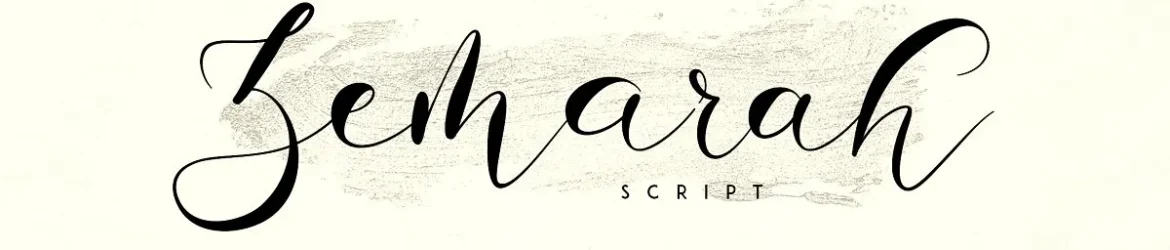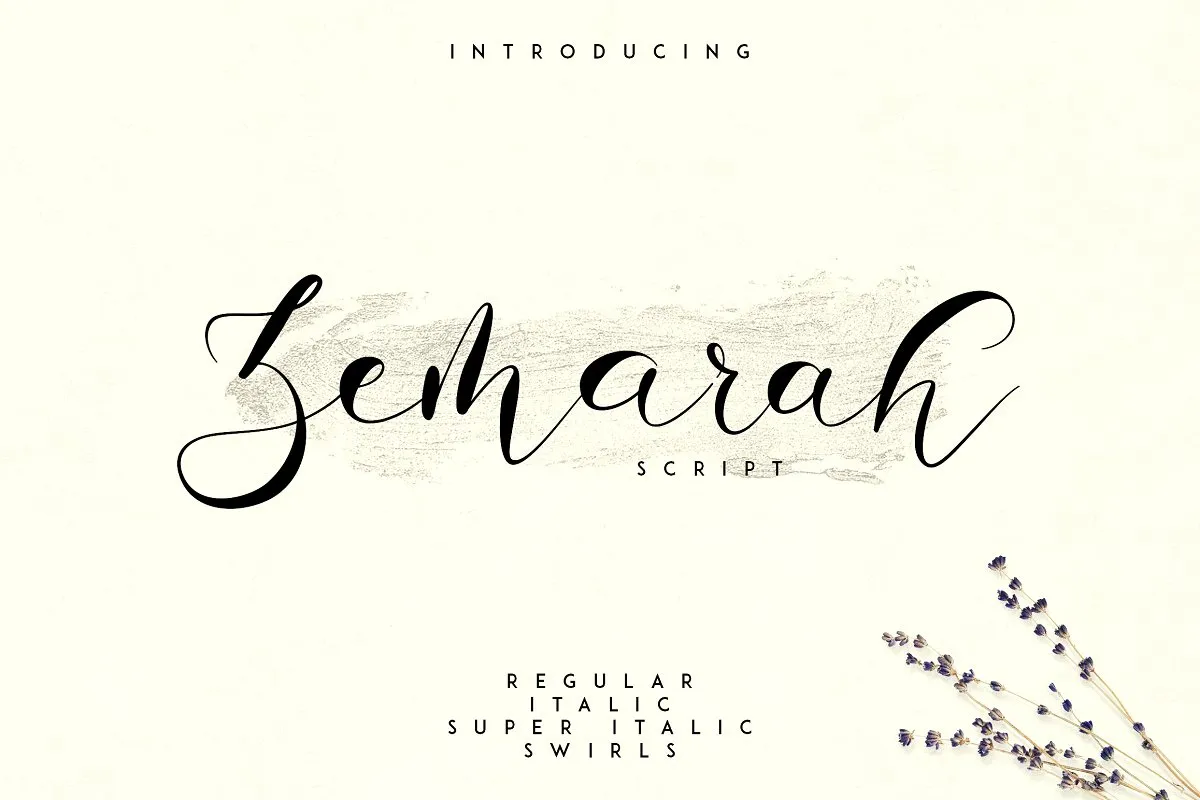
Zemarah Script Font – Fonte Grátis
Zemarah Script Font
A Zemarah Font é uma nova criação do design de Hamilton, oferecendo ao usuário um estilo elegante de calligrafia que se destaca por sua simplicidade e classe. Esta fonte foi pensada para ser simples e única, não sendo apenas mais um tipo de letra elegante. O designer introduziu três estilos nesta fonte: chamadas com borbulhantes e suavidades, além do apoio multilíngue que a torna ainda mais versátil. O estilo da Zemarah é tão singular que se destaca em grandes e pequenos tamanhos de texto. É uma opção ideal para designers gráficos e escritores, que buscam adicionar um toque único e sofisticado ao seu projeto visual. Com o Zemarah, você pode experimentar diferentes texturas e sensações em seus projetos com uma fonte versátil que vai desde as letras mais sutis até os espaçamentos mais amplos. Adquirir a Zemarah Font é garantir um estilo único para suas obras de design, tornando-a ainda mais singular e sofisticada. Um elemento que o distinguirá dos outros tipos de letra é seu suporte multilíngue, permitindo que você trabalhe com uma variedade de idiomas ao mesmo tempo sem perder a personalidade da fonte. Sem dúvida, a Zemarah é um ótimo investimento para qualquer designer buscando adicionar uma mão cheia de originalidade e sofisticação aos seus projetos visuais.